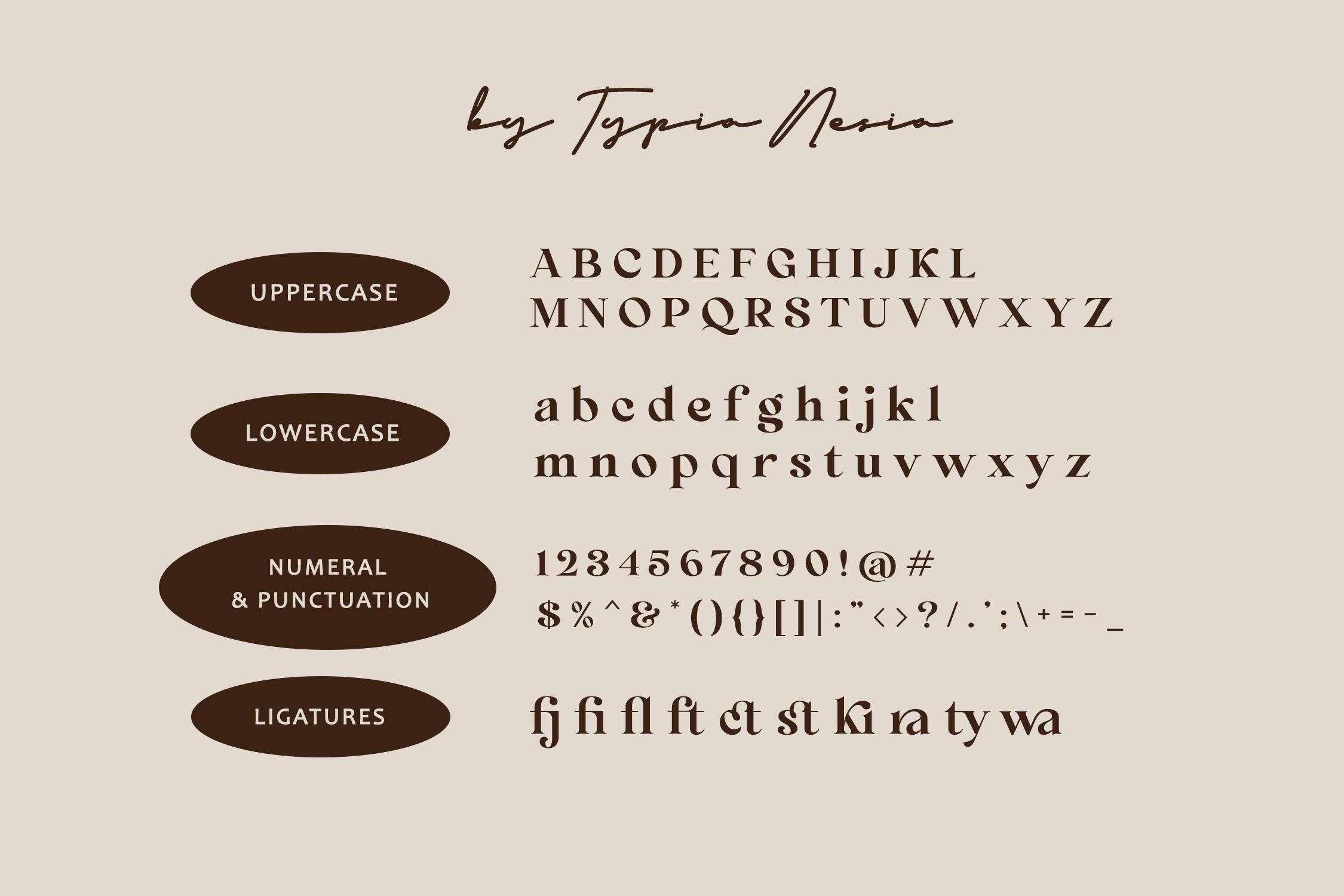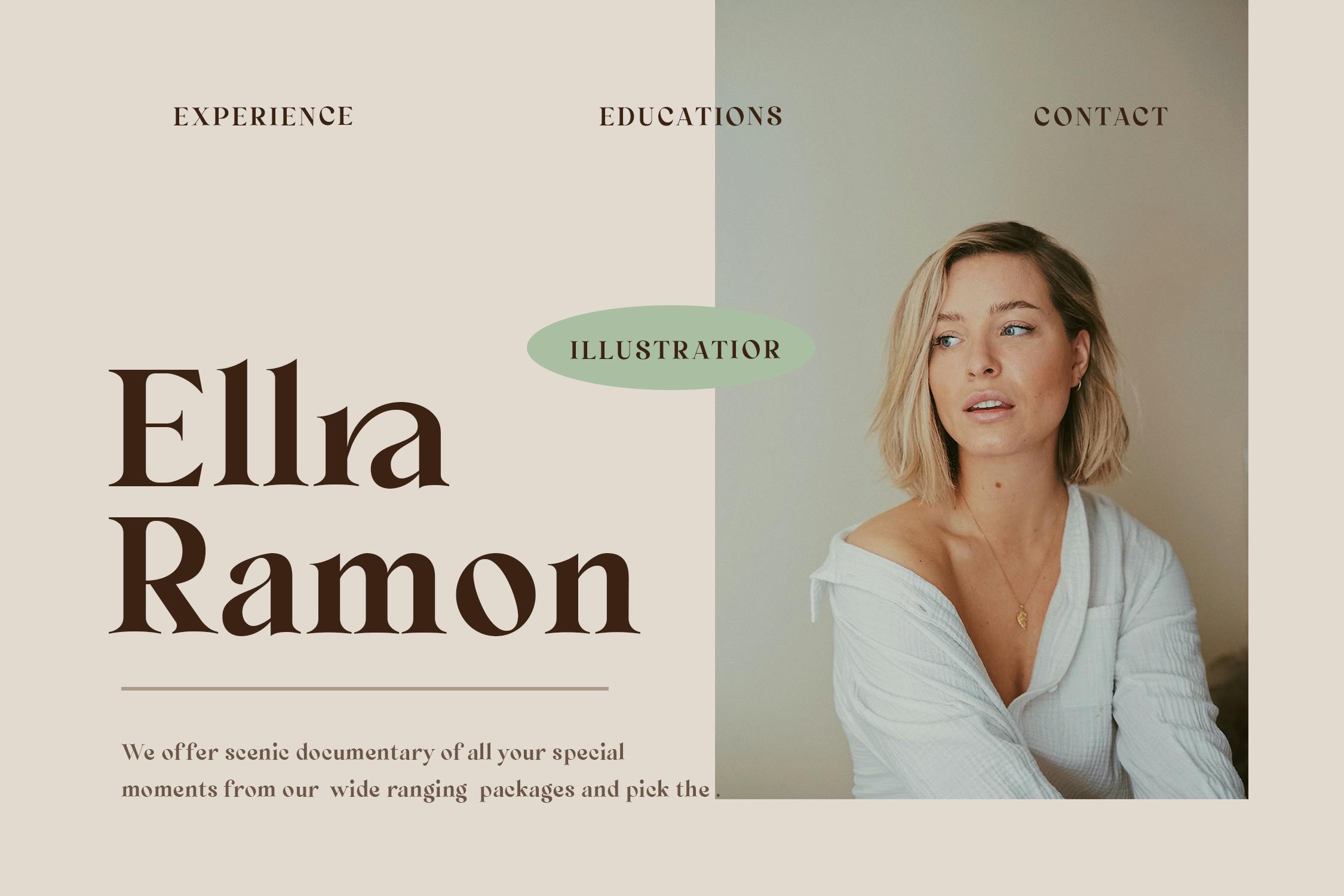
Kawai Craft - فونت نمایش کلاسیک و رترو با طراحی سرسیف و bold.
فونت Kawai Craft شامل برخی لیگاتورها است که به شما این امکان را میدهد تا ترکیبهای زیبا و جذاب برای طراحی تایپوگرافی خود ایجاد کنید. این فونت برای نیازهای طراحی مختلف مناسب است: لوگو، برندینگ، طراحی تبلیغات مدرن، طراحیهای وینتج، برندهای ماجراجویی و کوهنوردی، موسیقی هاردکور، انیمیشن یا فیلم، لوگوها، پوسترهای تابستانی رترو، عنوان جلد کتاب / رمان، طراحی ویرایشی، وبسایت / وبلاگ، کارت و هر نوع نیاز به حروفنگاری ایتالیک.